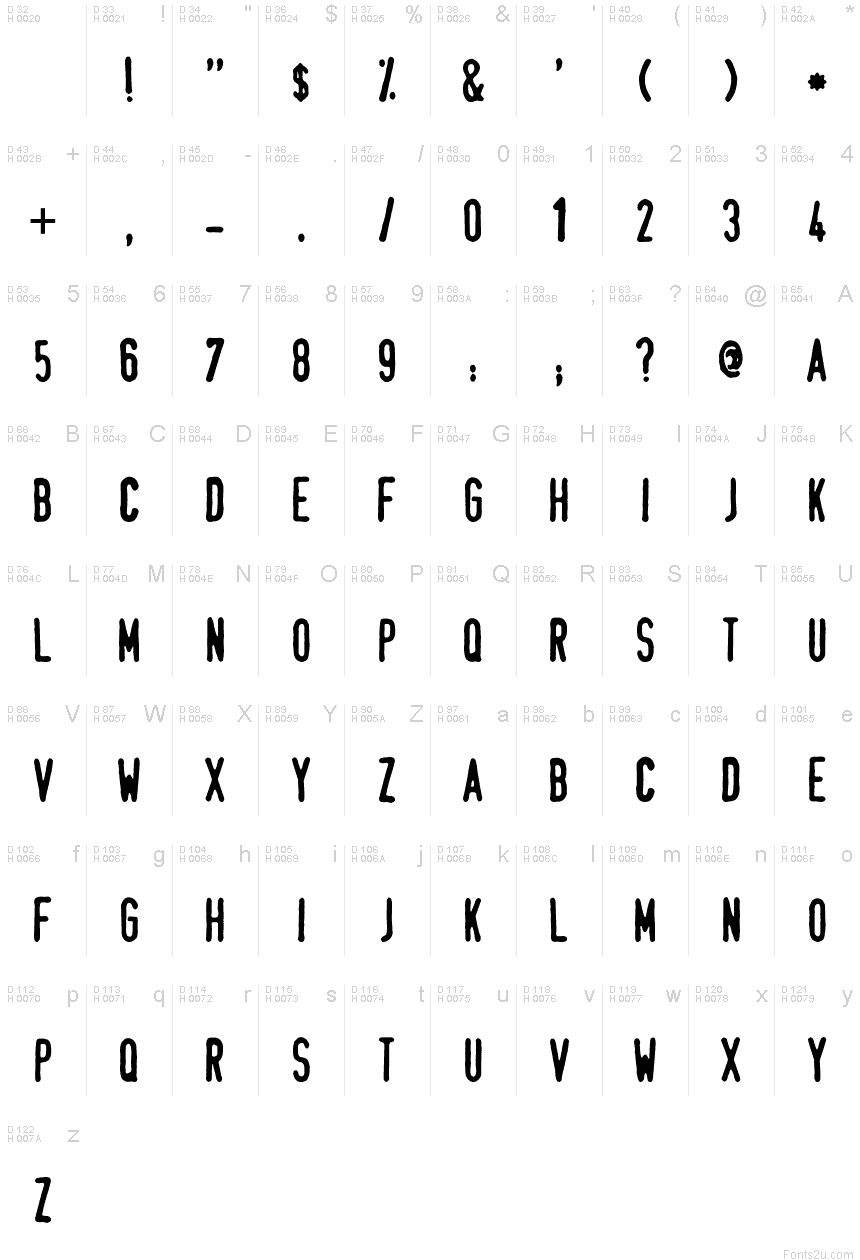
Stamp to darmowy font typu display, który ma w sobie bezpośredni, „prasowany” wygląd starych, zatłuszczonych liter. Wielkie litery są ciężkie i lekko przetarte, a zaokrąglone rogi oraz nierówne krawędzie sprawiają, że font nie wygląda zbyt sterylnie ani cyfrowo.
Świetnie pasuje do projektów, które mają sprawiać wrażenie rękodzieła, a nie idealnie czystej typografii: tytułów na plakatach, okładek płyt, opakowań, menu barowych, ulotek oraz krótkich znaków graficznych. Jako darmowe pismo sprawdzi się również w czołówkach, na okładkach czy w monogramach, gdzie te grube, „zatłuszczone” wielkie litery przyciągają wzrok nawet w pojedynczych słowach.